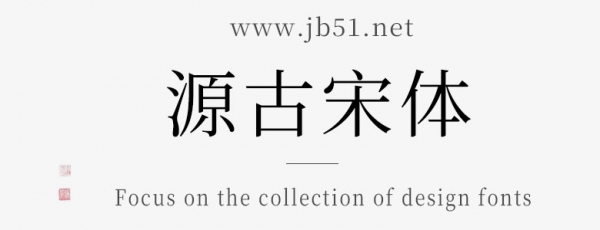
源古宋體是一款不錯(cuò)的藝術(shù)字體,宋體基于思源宋體改造,擴(kuò)B區(qū)的字取自文津宋體,具有很好的視覺感,適合應(yīng)用于藝術(shù)設(shè)計(jì)、平面宣傳設(shè)計(jì)、網(wǎng)頁設(shè)計(jì),書法字帖等領(lǐng)域,需要的朋友可以前來本站下載。
在工具包做出發(fā)布了兩款古籍規(guī)范的字體源古黑體與源古宋體,黑體基于思源黑體改造,擴(kuò)B區(qū)的字取自遍黑體。宋體基于思源宋體改造,擴(kuò)B區(qū)的字取自文津宋體。
得益于思源豐富的地區(qū)字形,拆拆湊湊很方便就可以改出一個(gè)古籍表版本。而關(guān)于那些部件不統(tǒng)一的字,我有選擇性地擅自進(jìn)行了統(tǒng)一。